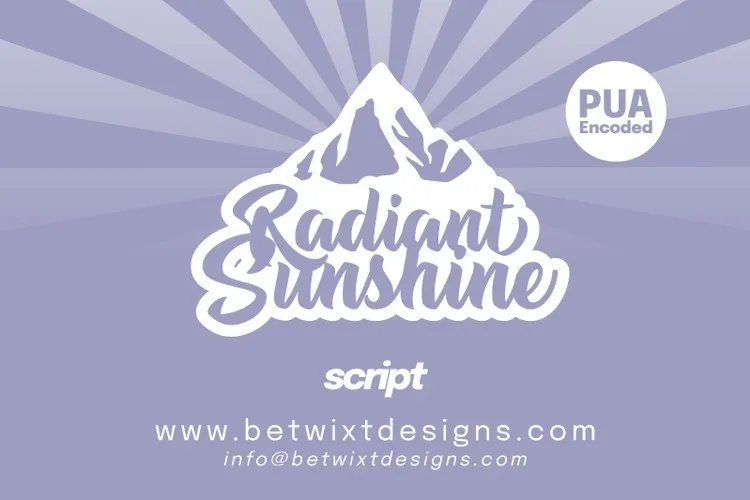
A “Radiant Sunshine Font” é uma tipografia urbana que lembra o estilo de letras logotípicas de antigas marcas. Este script foi projetado pela Betwixt Designs para ajudar a criar estilos de logomarcas ou grafismos para seus clientes e marca, bem como para as diversas aplicações gráficas em seu projeto, desde os selinhos até o material impresso e da própria camiseta. Ideal para quem busca um tom amigável e moderno que reflete a essência luminosa do sol nascendo. Com uma aparência vibrante e colorida, esta font oferece uma maneira de dar vida aos seus projetos digitais e presenciais. Seja criando um logo atraente ou um design gráfico sofisticado para sua identidade visual ou arte digital, você certamente encontrará no “Radiant Sunshine Font” uma solução perfeita para seu próximo projeto.